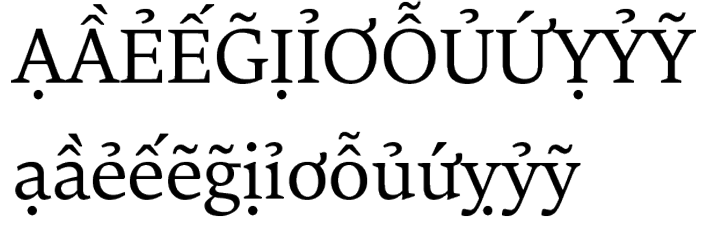
【Role Proの文字セットの拡張】
Role Proファミリーは、2019年に欧文スーパーファミリーとしてラテンアルファベットを用いる98言語に対応したフォントとしてリリースされました。その後、モリサワでは独自の欧文書体の文字セット「Pro」を拡張し、ベトナム語とグアラニ語を加えた合計100言語に対応した欧文書体を順次リリースしています。この2023年の改訂により、Role Proファミリーでも100言語に対応した文字セットをご利用いただけるようになります。文字セットの詳細につきましては「欧文書体の文字セットについて」をご確認ください。
【グリフの追加】
以下のようなグリフが追加されています。
ベトナム語・グアラニ語対応用グリフ例
Role Serif Text Pro Regularでの例となります。
ベトナム語とグアラニ語に対応したグリフの追加を行います。
なお、追加グリフ以外のグリフに変更がなく組体裁への影響もありません。